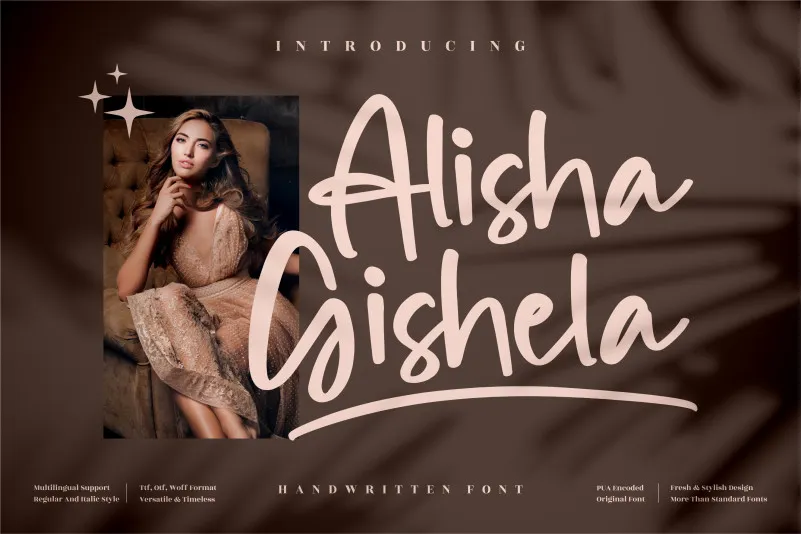
Alisha Gishela Font – Download Grátis
A Alishah Gisela Font é uma fonte escrita a mão perfeita para projetos variados, desde criações de logotipos até cartões de visita e aniversários. Suavemente adaptada à sua estética natural e autêntica, essa fonte transmite um toque personalizado ideal para qualquer projeto que busque um tom elegante e único. Com sua característica de escrever a mão, ela é perfeita para design de móveis de consumo, embalagens de produtos, pacotes de chá, revistas e livros, camisas personalizadas e outros itens de luxo como sacolas e adesivos de papelão. Além disso, sua delicada escrita permite uma versatilidade incrível. Use-a em qualquer lugar que você precise de um toque humano: rótulos para seus produtos, fotografias, marcas nos seus projetos gráficos ou até mesmo para aniversários e eventos especiais. A Alishah Gisela Font não apenas oferece a oportunidade de adicionar um toque especial ao seu design, mas também permite que você transmita uma história única através da escrita de sua própria mão.